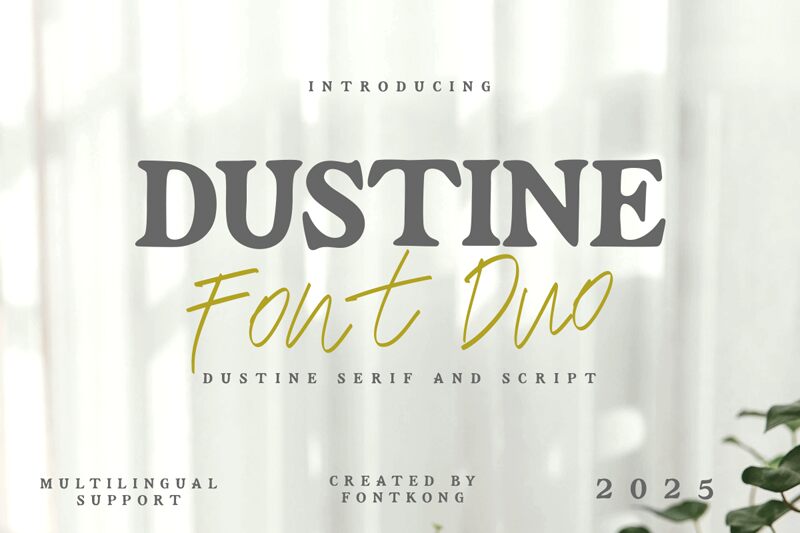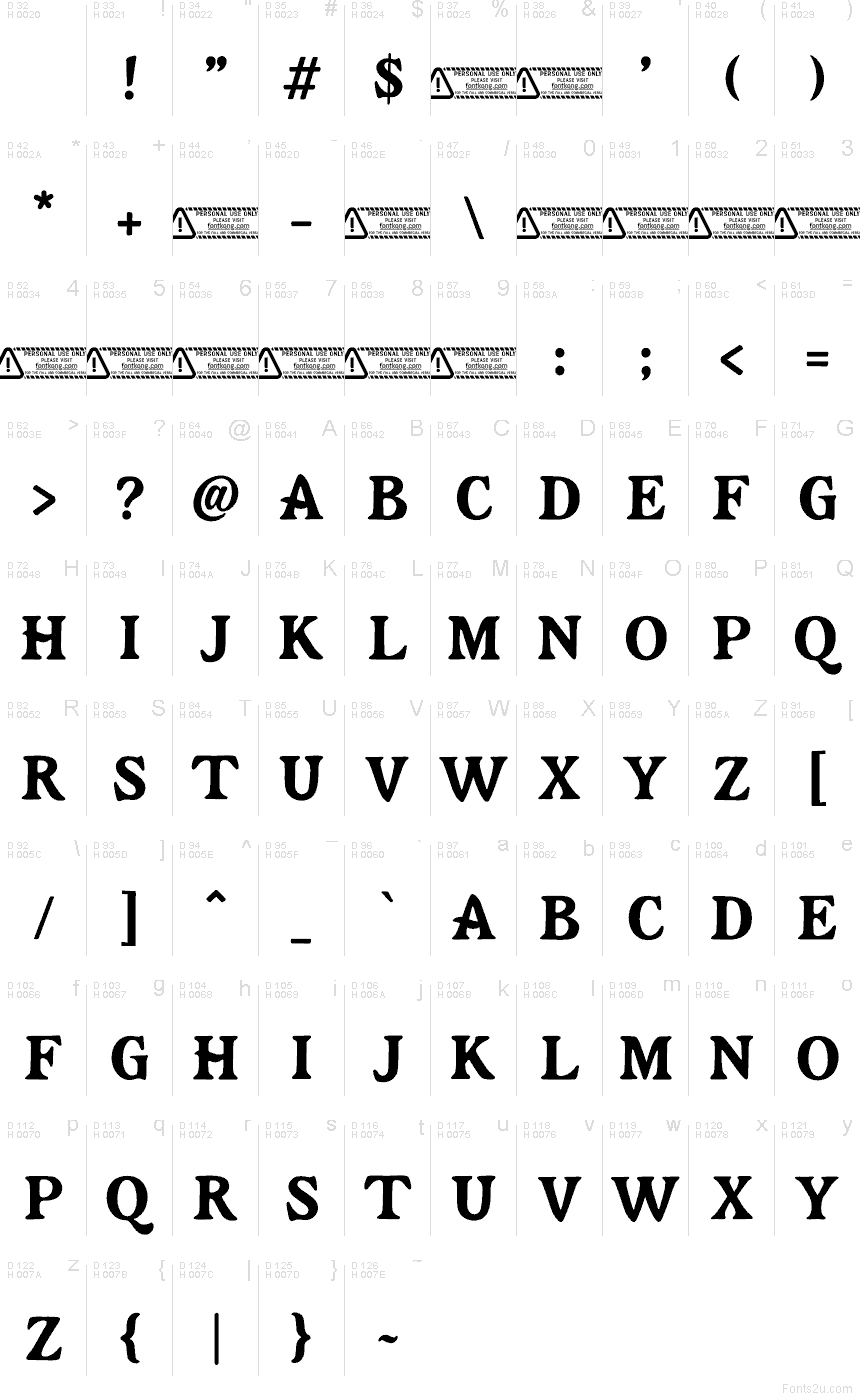
Dustine Serif Regular
Dustine Serif von Kong Font ist eine kostenlose Vintage-Serifenschrift mit breiten, skulpturalen Buchstaben und einem Hauch von Märchenbuch-Charme. Die Großbuchstaben bestechen durch schwere, abgerundete Serifen und sanfte, nach innen gewölbte Kurven, die der Schrift eine würdevolle Note verleihen, ohne steif zu wirken.
Sie eignet sich hervorragend für Verpackungsdesigns, Café-Branding, Plakatüberschriften, Buchtitel und Titelkarten, bei denen ein klassischer Charakter mit einer warmen Ausstrahlung gefragt ist. Als kostenlose Schrift funktioniert sie zudem wunderbar für Monogramme und kurze Cover-Texte, da die breiten, wie geschnitzt wirkenden Buchstaben auch bei wenigen Zeichen alle Blicke auf sich ziehen.